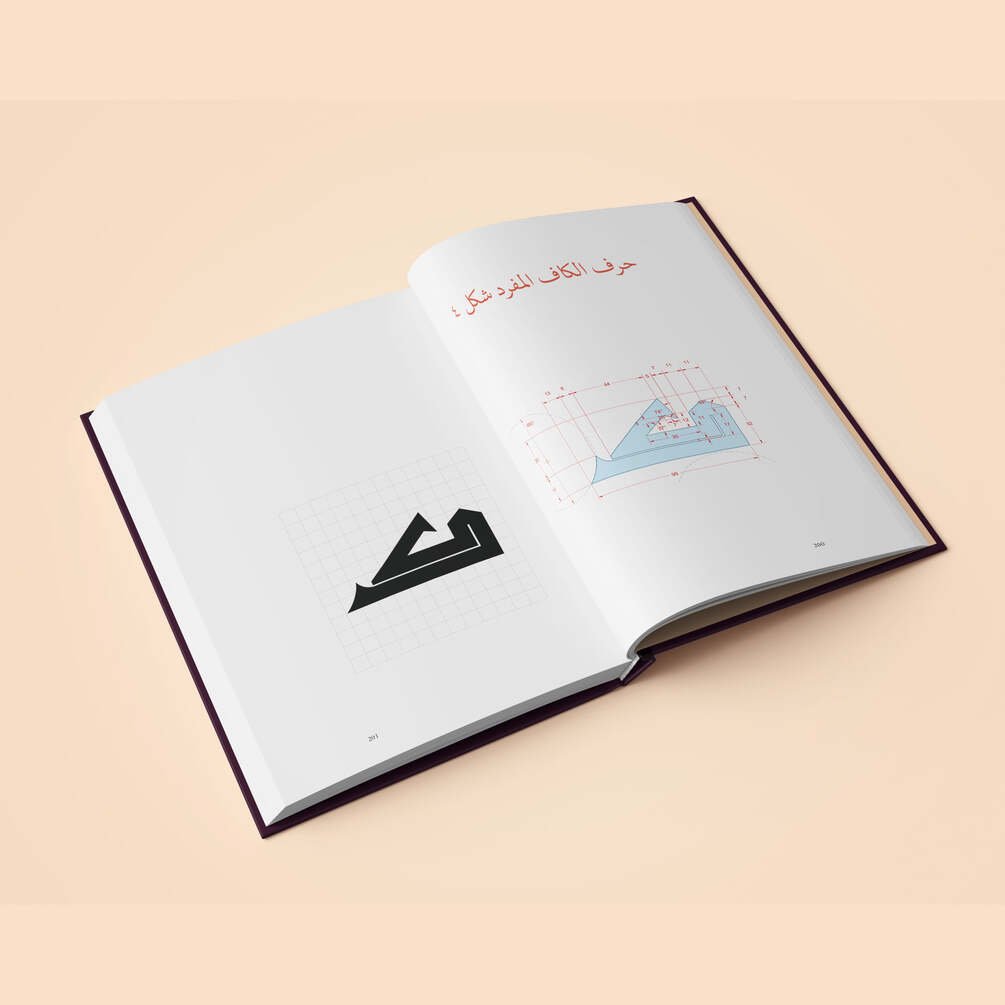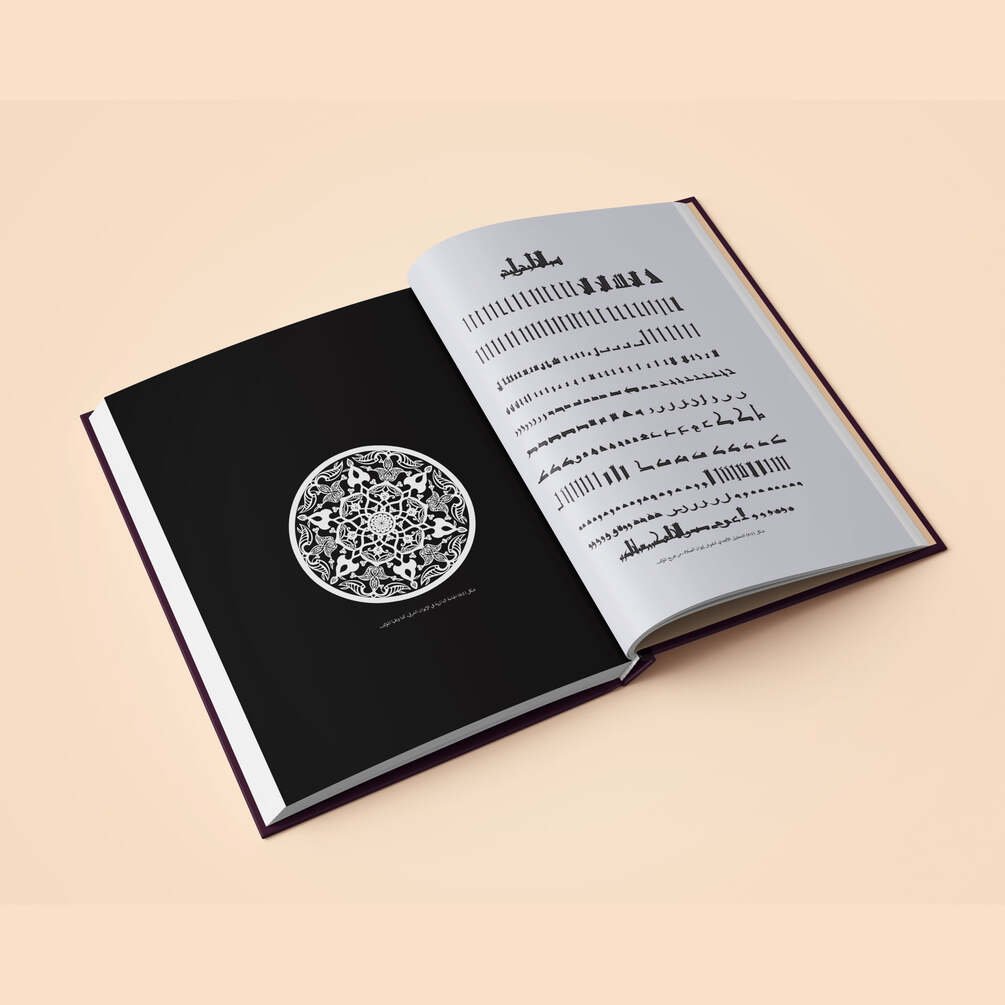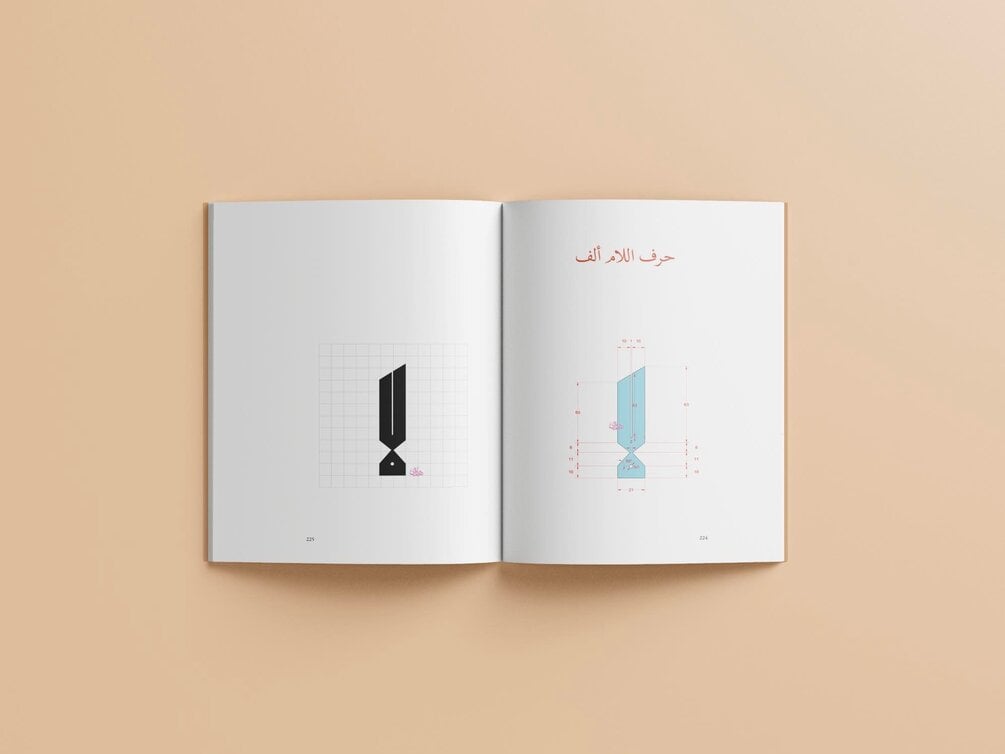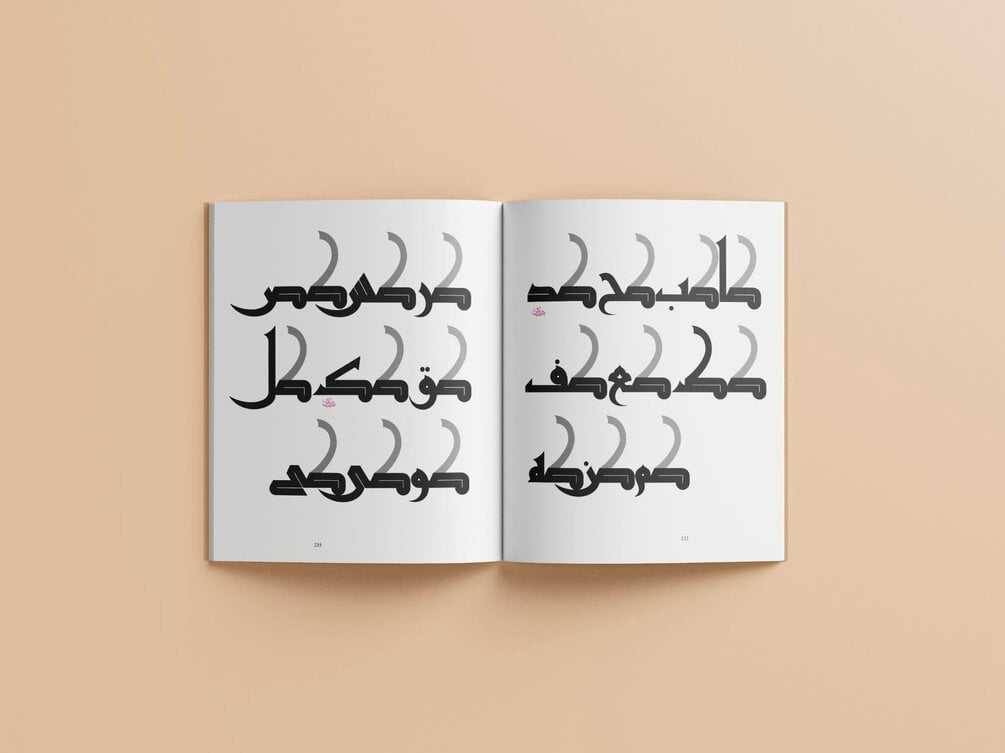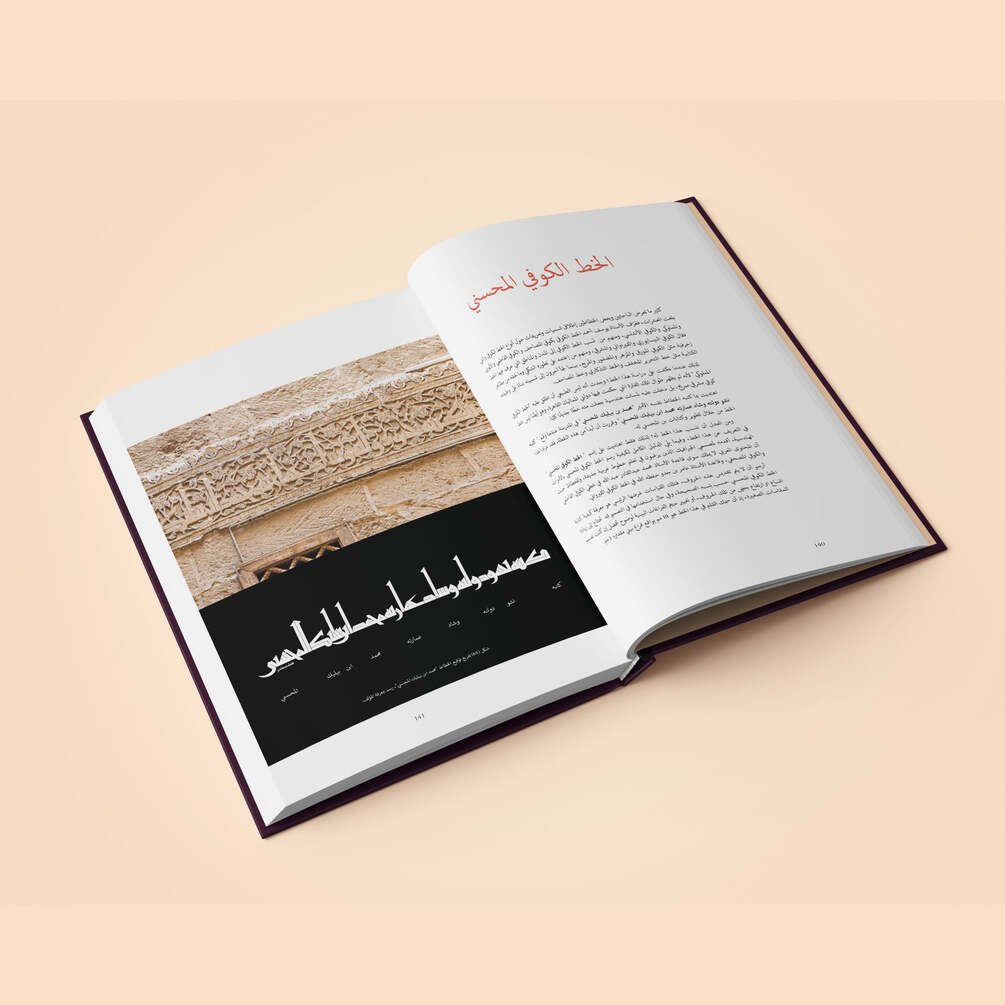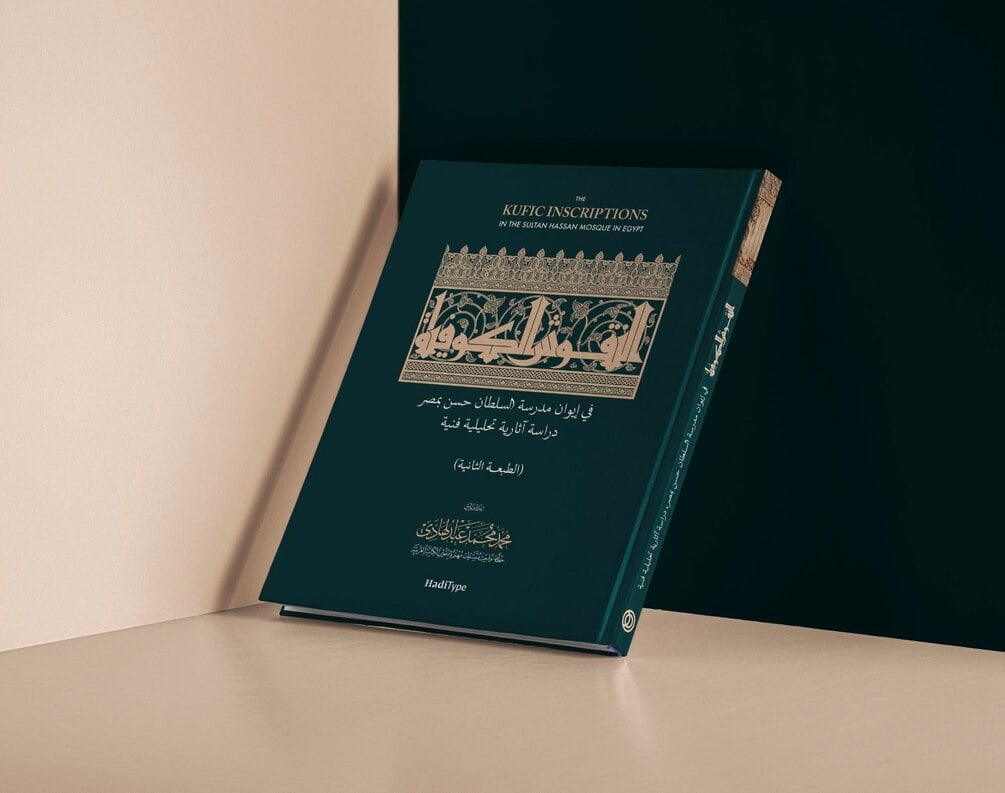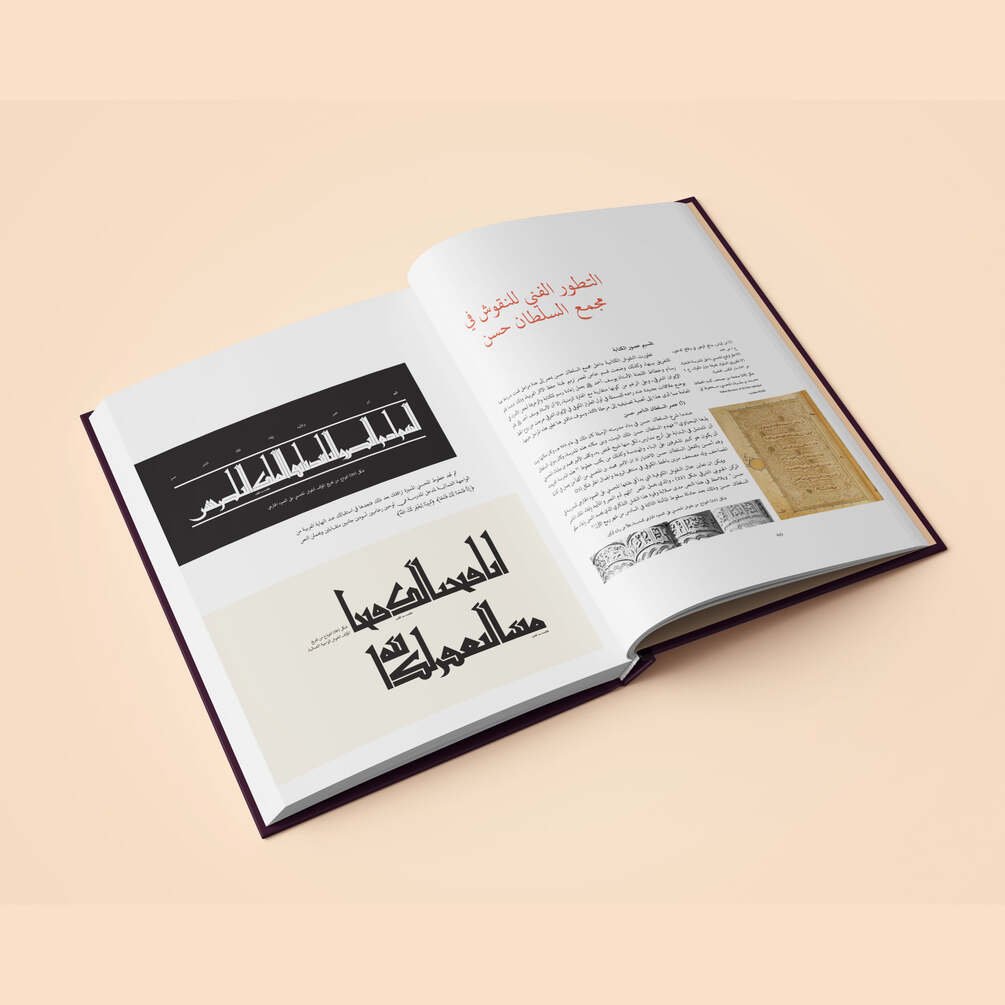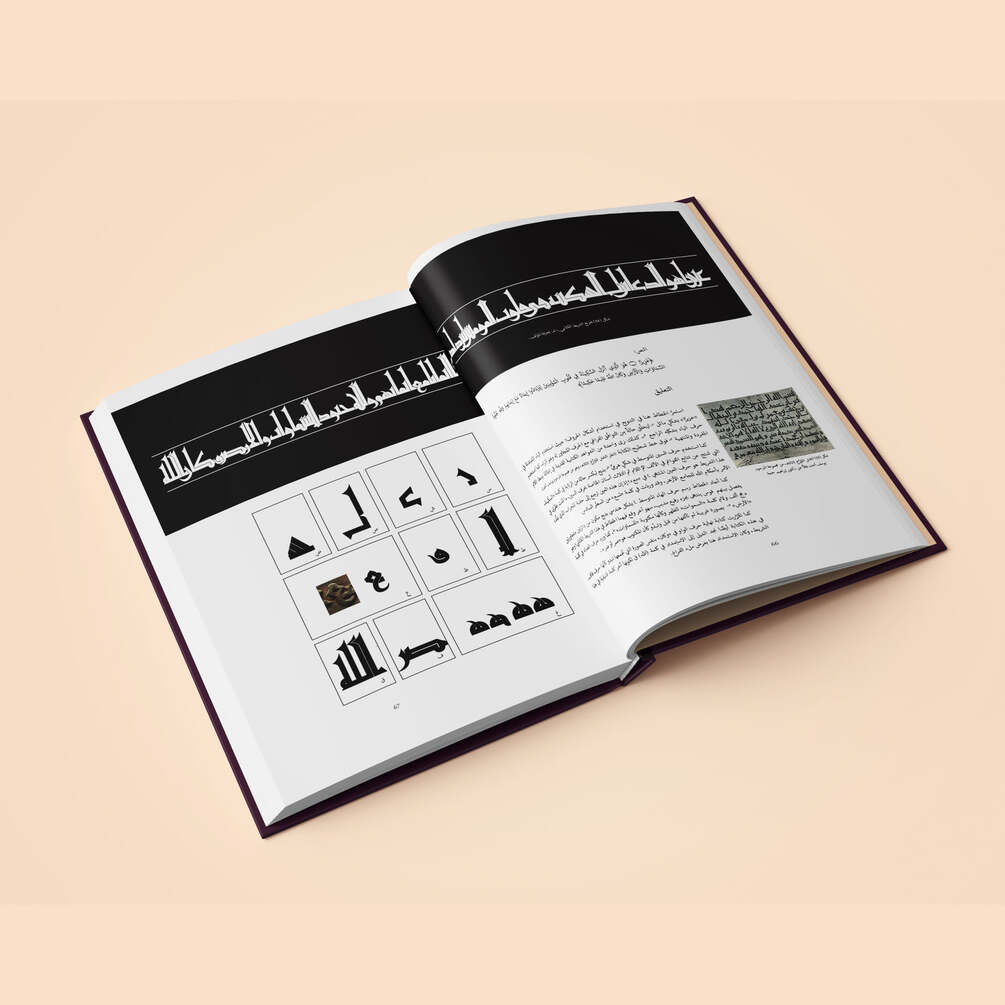
كتاب النقوش الكوفية في إيوان مدرسة السلطان حسن
كتاب «النقوش الكوفية في إيوان مدرسة السلطان حسن».
الطبعة الثانية والمزيدة
- الكتاب يعتبر الدليل الأساسي لأعظم نقوش كوفية في دولتي المماليك اقدمها لكم في حزمة مدمجة جميلة.
- تحليل أبجدي كامل لكل النقوش الكوفية في الإيوان الشرقي.
- • باب خاص لكل الحروف المتصلة للخط الكوفي المحسني ليكون مشق تعليمي متكامل.
- • المشق والدليل الكامل الخط الكوفي المحسني ويعتبر الدليل الخاص للمصممين والخطاطين وطلاب التصميم الجرافيكي والفنون التطبيقية والجميلة
- • إضافة التحليل الهندسي لحرفي «لام ألف» وردتا في نقوش المدرسة الحنفية، وتعتبر هذه أول إضافة لهم ترى النور كتحليل هندسي.